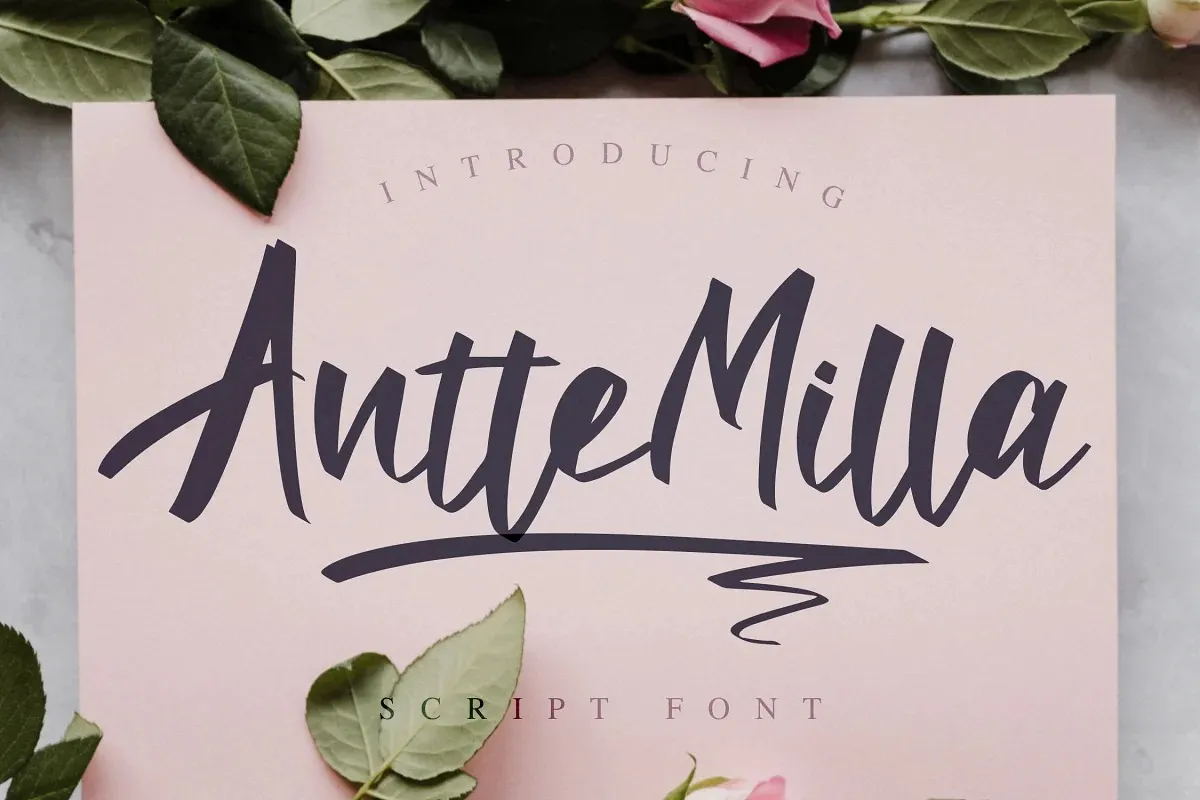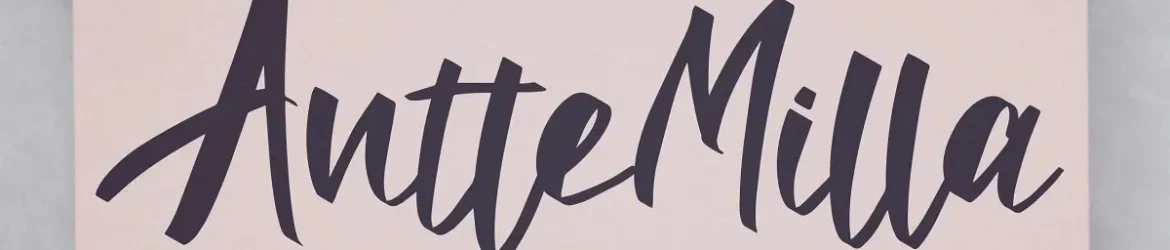
Antte Milla Font – Download Grátis
A Antte Moe é uma fonte script curiosa que surgiu dos desenhos de caneta a esmalte. Ela foi criada com uma abordagem audaciosa, incorporando traços de raspas e formas curvilíneas nas letras, proporcionando um visual elegante e único aos seus designs. Esta fonte é perfeita para fazer preview’s, capas e até mesmo estampar camisetas, adaptando-se a diversas necessidades gráficas. Seu estilo delicado e suave enriquece os produtos digitais, tornando-os ainda mais atraentes e únicos. Antte Moe é uma escolha perfeita para quem deseja dar um toque pessoal aos seus projetos de design.